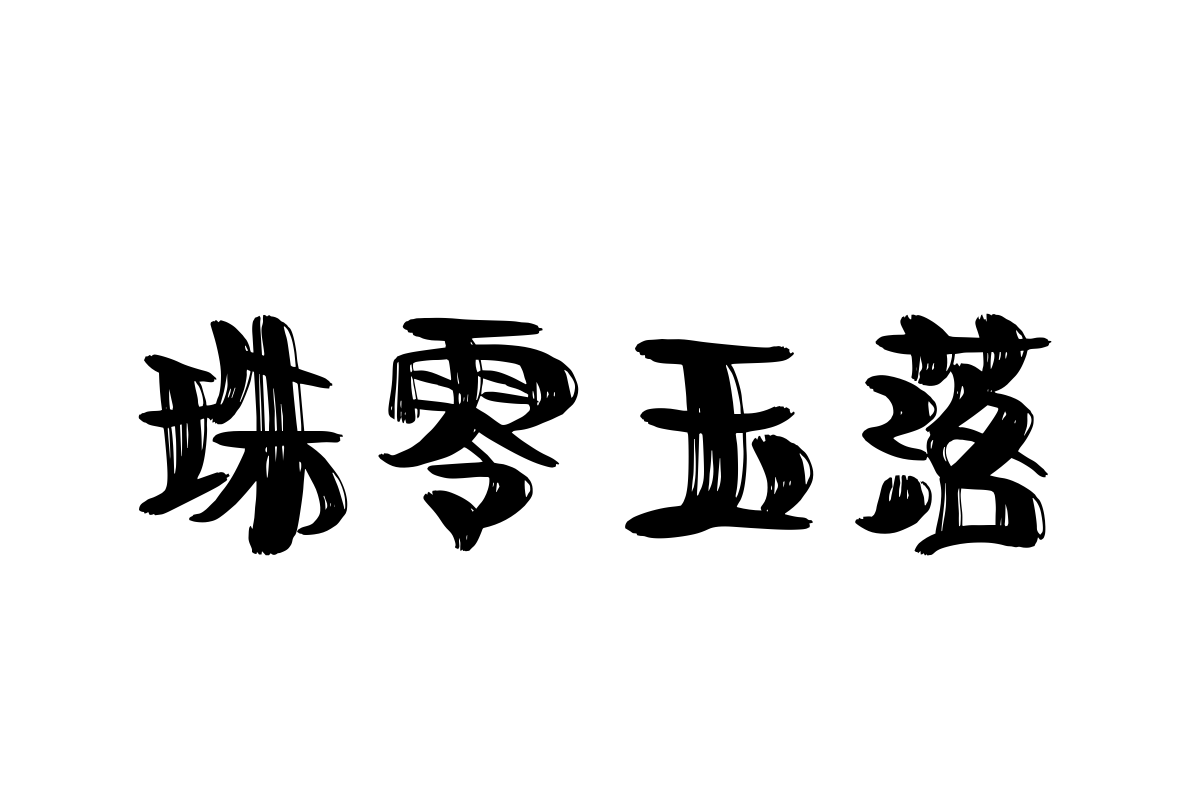
汉仪喵魂梦境是一款具有独特风格的字体,它采用了独特的笔画和结构,使得每一个字符都充满了个性和魅力。这款字体适用于各种设计场景,无论是广告、海报、包装还是网页设计,都能展现出其独特的美感。
汉仪喵魂梦境的笔画流畅而有力,每个字都像是在跳跃着,给人一种充满活力的感觉。它的结构紧凑而有序,使得整个字体看起来既紧凑又富有层次感。这种独特的风格使得汉仪喵魂梦境成为了一种非常受欢迎的字体选择。
此外,汉仪喵魂梦境还具有很高的可读性。虽然它的笔画复杂,但每个字符的大小和间距都经过精心设计,使得阅读起来既舒适又清晰。这使得汉仪喵魂梦境不仅适合用于设计,也适合用于日常阅读。
总的来说,汉仪喵魂梦境是一款非常独特且优秀的字体。它既有个性又有美感,无论是用于设计还是用于阅读,都能展现出其独特的魅力。